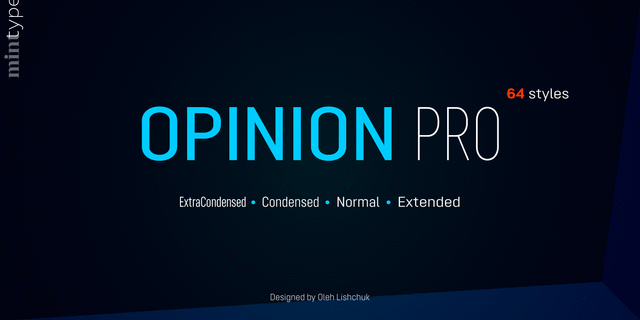
Opinion Pro — геометрический гротеск, состоящий из 64 начертаний. Он содержит 4 градации ширины (ExtraCondensed, Normal и Extended), каждая из которых состоит из 8 весов и соответствующих курсивов. Жесткие кривые и выраженные вертикальные штрихи делают Opinion Pro подходящим как для акциденции, так и для набора, в частности для технических задач и навигации.
Opinion Pro поддерживает большое количество языков, включая все европейские языки, основанные на латинице, основные кириллические языки, а также казахскую кириллицу. Поддержка OpenType включает, помимо прочего, 4 набора цифр, капитель, верхние буквенные индексы.
Шрифт разработал Олег Лищук в студии Mint Type в 2017 году.